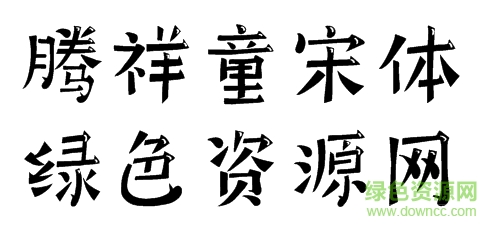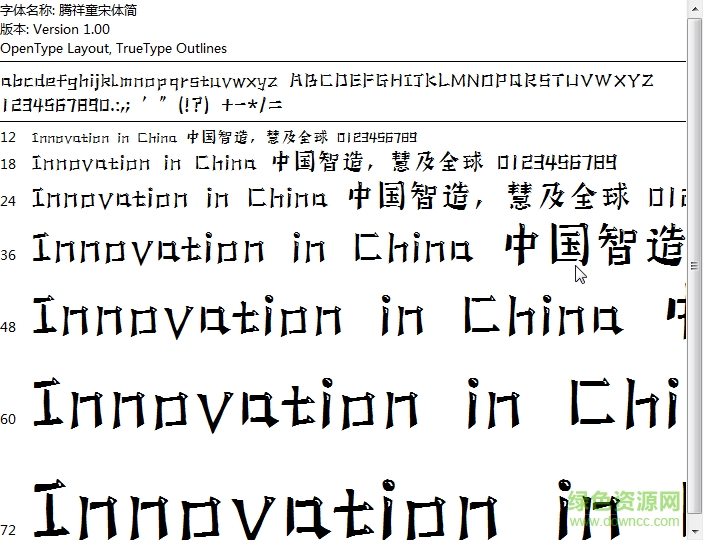
騰祥童宋體是騰祥字庫推出的一款全新的兒童字體,采用了宋體的精髓,更顯童稚有趣,整體造型虛實(shí)相間,效果獨(dú)特,有著極佳的視覺體驗(yàn),來綠色資源網(wǎng)免費(fèi)下載吧!
此款字為美術(shù)字。風(fēng)格鮮明、特點(diǎn)突出。筆畫拙、巧結(jié)合結(jié)構(gòu)散落有序。基本筆畫帶有宋體字風(fēng)格,特別是點(diǎn)、橫、豎、折角等凸顯宋體特征。結(jié)構(gòu)上則完全打破宋體的規(guī)整與規(guī)范,從而形成一款隨性且有趣味的字體。本款字在不影響閱讀的前提下盡顯其特性。本作品可適用于印刷出版兒童讀物、包裝設(shè)計(jì)、廣告設(shè)計(jì)、網(wǎng)頁設(shè)計(jì)等。
騰祥童宋體簡是一款設(shè)計(jì)精美的手繪美術(shù)字體,筆畫間相互呼應(yīng)且張弛有度,字面大小均勻,筆畫規(guī)范,且字庫完整,非常有手寫感,可以廣泛應(yīng)用于廣告設(shè)計(jì)、宣傳海報(bào)、ppt、影視制作以及任何使用文字的領(lǐng)域!